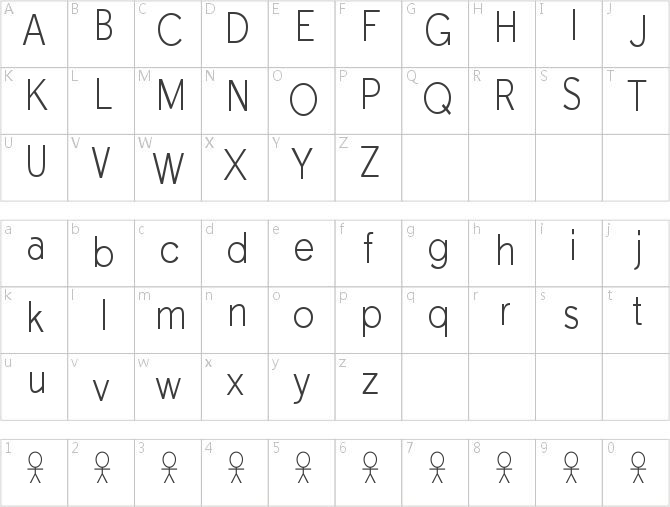
Tabarra NarrowLight 詳情頁
字體名稱: Tabarra
Tabarra NarrowLight
Tabarra NarrowLight字體字庫是一款讓人賞心悅目、百看不厭的英文字體,適合各類廣告和產品包裝設計應用,字體大小0.05MB,格式為ttf字體,上傳用戶是青檸檬,作者/版權方為未知